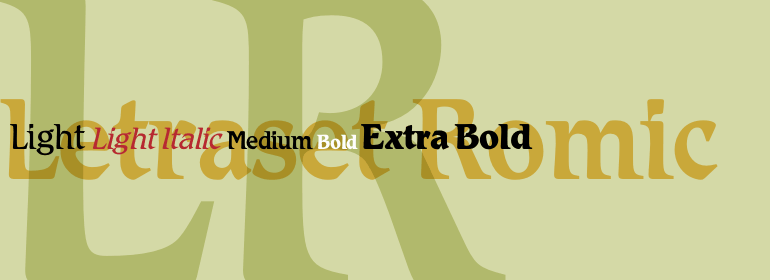
Letraset Romic™
Letraset Romic™,这款字体结构工整、笔画清晰,兼顾美观与易读性,适用于标题、正文、海报、包装、LOGO 等多种场景。字形优雅稳定,风格百搭耐看,适配日常排版与创意设计,让文字呈现更舒适、更具质感。Letraset Romic™一笔一画,皆是细节,以均衡的比例、流畅的线条打造舒适视觉体验,字形端正大气,风格简约现代。无论是商业设计、品牌宣传还是日常排版,都能轻松驾驭,让文字更有格调与力量。Letraset Romic™字体下载。
字体品牌: ITC(Monotype) 设计师:Brignall,Colin 字体分类:衬线体 字体属性:外文 字符集:Unicode 发布时间: 2018
Letraset Romic was designed by Colin Brignall and released in 1979. The Letraset Romic font family can be used for short texts and as a headline face.